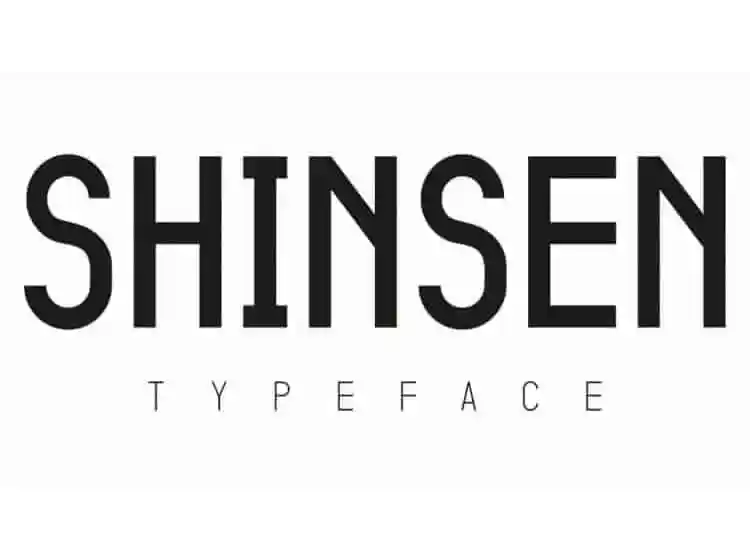
A Shinsen Sans Serif é uma fonte sem serif casual e limpa que oferece três estilos únicos. Ela foi criada por Retr0 através do site 99designs, e a caracteriza-se como um tipo geométrico para impressão em grande tamanho. Essa fonte tem um estilo atraente com um toque industrial. A família de caracteres da Shinsen Sans Serif inclui três pesos variados que são ideais tanto para títulos quanto para subtítulos, legendas de revistas, posters e outros usos de exibição. Seja para tornar seu site ou qualquer projeto visual mais atraente e moderno, essa fonte será um ótimo escolha. Se você busca uma opção sem serif que seja casual e clean, não hesite em experimentá-la nas próximas criações gráficas.